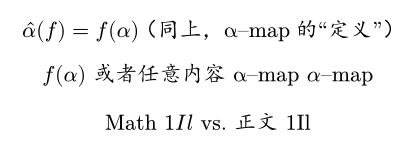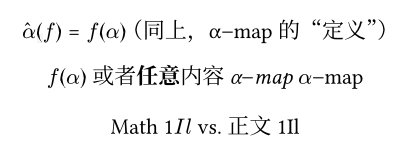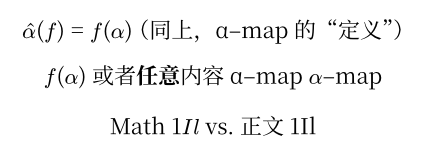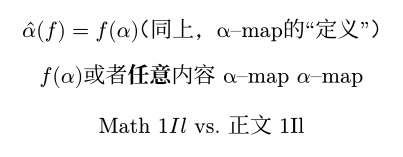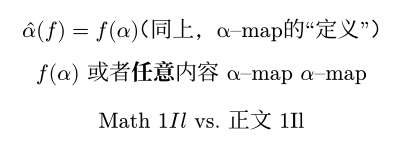
如何修改公式里的中文字体?
若不专门设置,公式中的中文通常是楷体:
✅ Typst 0.13 已改进
#5305 目前可以对不同字符分别设置不同的字体。
配置正文字体后,请继续设置数学公式的字体:
= hint: rendering may be poor西文字体,负责
123、abc、,"!、{}()等Libertinus Serif 是 typst 内置的字体,可换为其它西文字体。
中文字体,负责汉字和
,“”!等Source Han Serif SC 可换为其它中文字体。
数学字体,负责公式中的复杂排版
New Computer Modern Math 是 typst 内置的字体,可换为其它支持 OpenType 数学特性的字体。
若计划中西共用同一字体
可合并前两项,例如:
= hint: rendering may be poor注意这里第一处_α–map_没有倾斜,因为 Source Han Serif SC 缺少相应字形。
此外,不建议设置 #show math.equation: set text(fallback: false)。
如果你使用旧版本,请使用以下旧方案。
使用 regex("\p{script=Han}") 匹配中文。